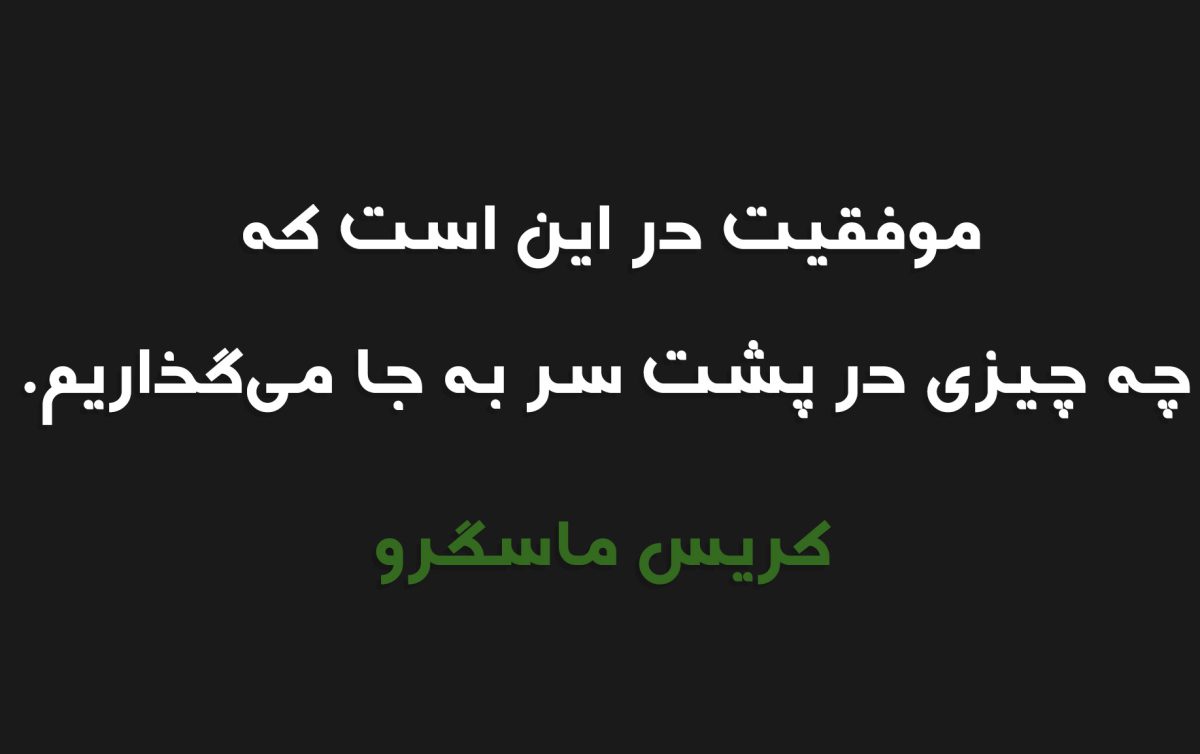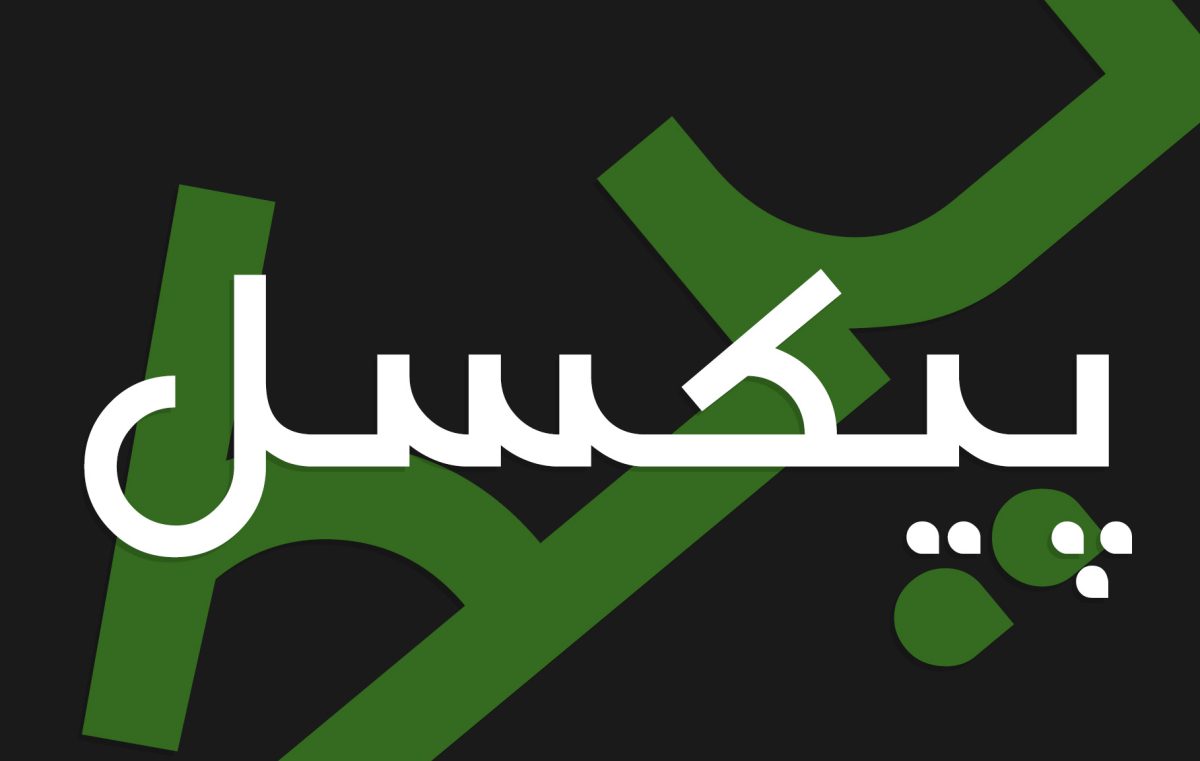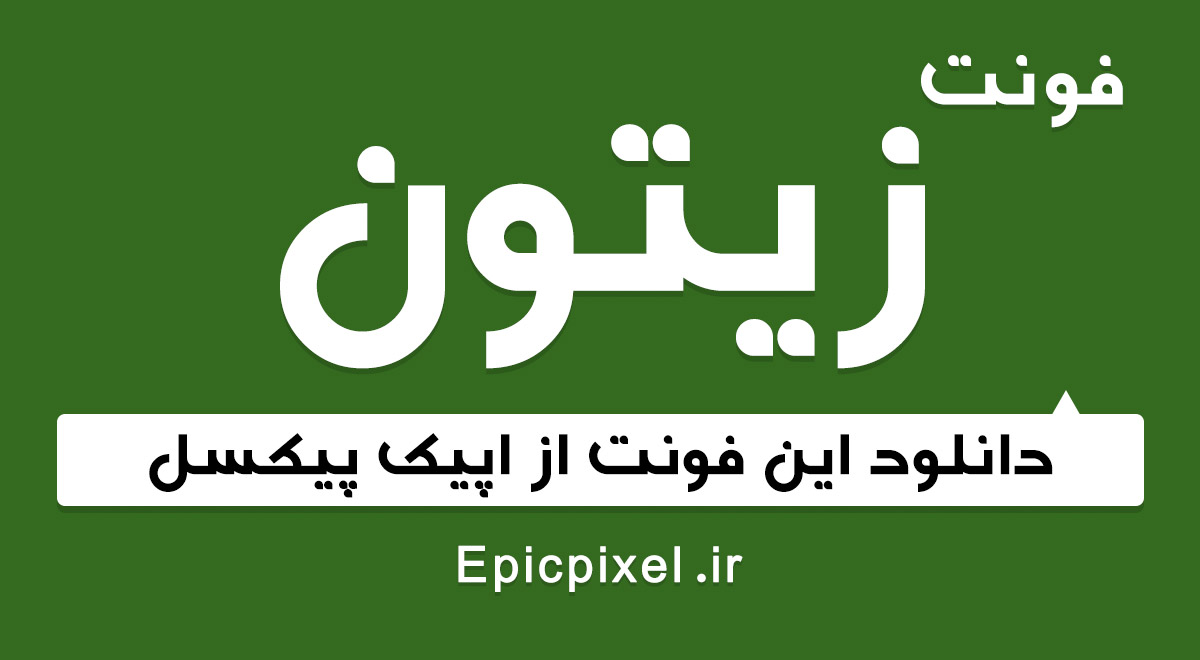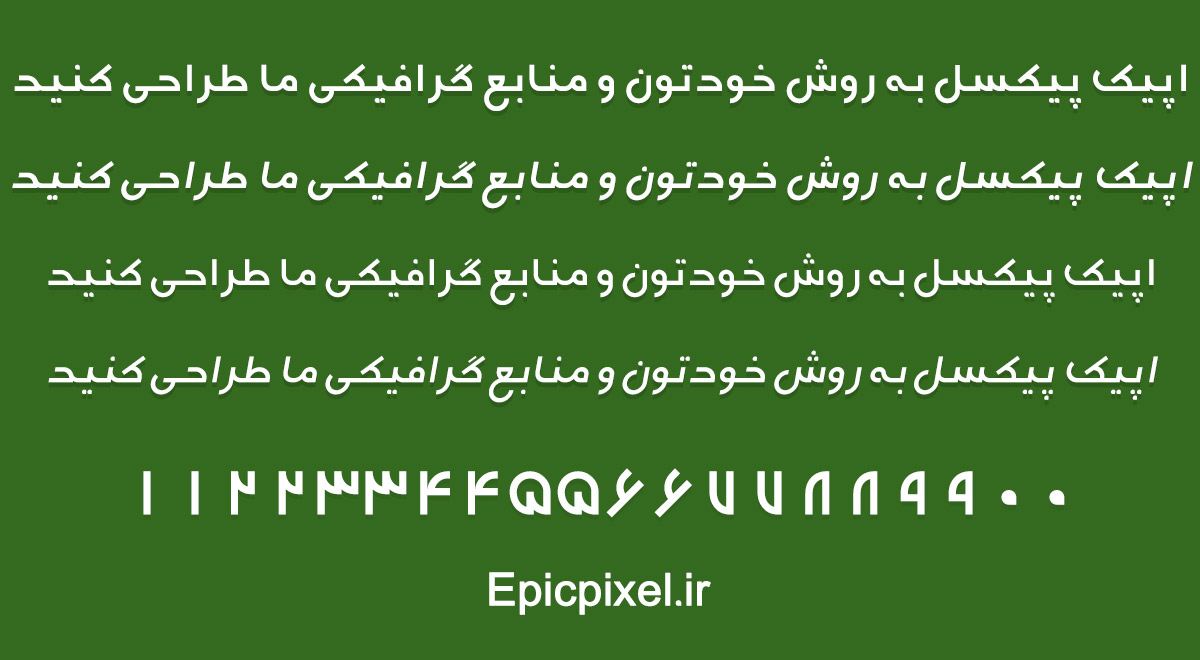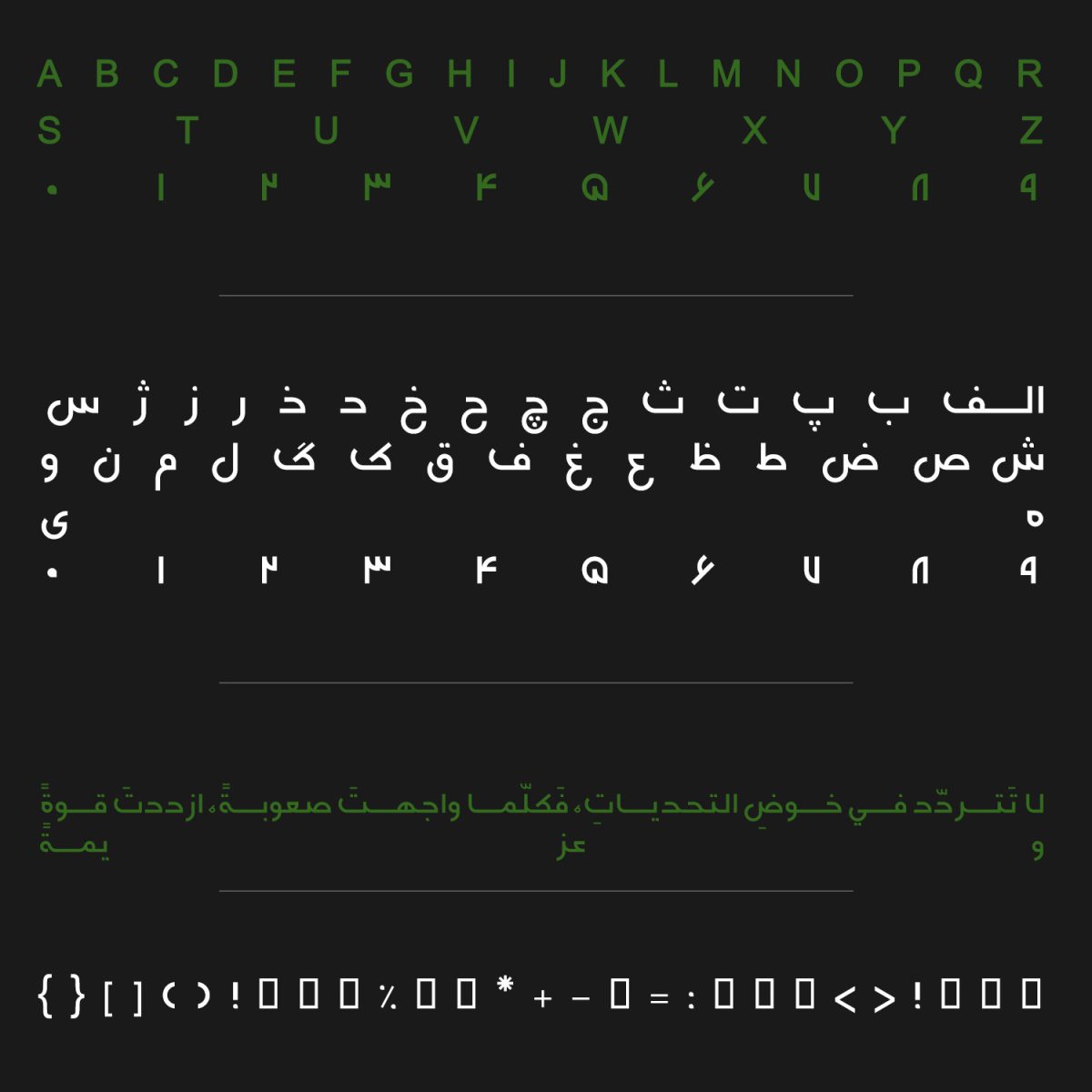
4 فونت زیتون فارسی Zeytoon
فونت فارسی زیتون، یک قلم دایره ای و فانتزی با طراحی زیبا و حرفه ای است که به صورت رایگان قابل دانلود می باشد. این فونت با پشتیبانی از تمام حروف و اعداد فارسی، در چهار حالت مختلف با اسامی متفاوت (F zeytoon Normal, IR Zeytoon Regular, W zeytoon Regular, Zeytoon Regular) ارائه شده است. فونت زیتون دارای خوانایی بالایی برای عناوین بوده و برای استفاده در لوگوتایپ، تایپوگرافی و انواع طراحی گرافیک، از جمله چاپ و امور تبلیغاتی، بسیار مناسب است. این قلم که قبلاً پولی بوده و هم اکنون رایگان شده، در فرمت TTF بر روی ویندوز، مک و موبایل قابل نصب و استفاده در تمامی نرم افزارهای گرافیکی است.
قلمی دایره ای، فانتزی و رایگان برای طراحی
فونت فارسی زیتون، یک قلم با ظاهر بصری متمایز و کارایی بالا برای طراحان است. این فونت با طراحی دایره ای و فانتزی خود، جلوه ای جالب و متفاوت به متون می بخشد و آن را برای پروژه هایی با حس خلاقیت و سبکی غیررسمی مناسب می سازد. این فونت زیبا و حرفه ای برای طراحی محسوب شده و یک فونت جالب و متفاوت برای خلق آثار خلاقانه است که می تواند به سرعت توجه مخاطب را جلب کند.
یکی از نکات قابل توجه در خصوص فونت زیتون، ارائه آن در چهار حالت مختلف با اسامی متفاوت است. این نسخه ها با نام های فونت اف زیتون نرمال (F zeytoon Normal)، فونت آی آر زیتون ریگولار (IR Zeytoon Regular)، فونت دبلیو زیتون ریگولار (W zeytoon Regular)، و فونت زیتون ریگولار (Zeytoon Regular) در دسترس هستند. این حالت های مختلف، نسخه های گوناگون این فونت را شامل می شوند، از جمله نسخه با پسوند IR که به عنوان “نسخه سالم” (اصلاح شده توسط شورای عالی اطلاع رسانی) معرفی شده است که از نظر فنی بهینه شده است. وزن آن عموماً معمولی – Regular می باشد که پرکاربردترین وزن برای بسیاری از طراحی ها است.
دانلودفونت زیتون به واسطه خوانایی بالا که دارد، به صورت ویژه برای استفاده در لوگوتایپ، تایپوگرافی و همچنین در عناوین مختلف بسیار مناسب است و پیام را با ظاهری دایره ای و دلنشین منتقل می کند و در اندازه های مختلف عملکرد خوبی دارد. این قلم یک فونت گرافیکی و حرفه ای برای انجام امور خاص طراحی و نیز برای طراحی های گرافیکی و چاپ به صورت کلی می باشد و ابزاری منعطف برای نیازهای متنوع است.
این فونت گرافیکی و حرفه ای دارای تمام حروف و اعداد فارسی است که امکان استفاده کامل از آن را در محتوای فارسی بدون هیچ نقصی فراهم می کند و آن را به ابزاری کاربردی برای طراحان فارسی زبان تبدیل می کند. فونت زیتون با فرمت ttf ارائه می شود که سازگاری بالایی با نرم افزارهای طراحی و سیستم عامل ها دارد و نصب و استفاده از آن را بسیار آسان می کند.
کاربردهای فونت زیتون در طراحی گرافیک و چاپ
با توجه به طراحی دایره ای و فانتزی، خوانایی بالا، و قابلیت استفاده در انواع نرم افزارهای گرافیکی، فونت زیتون کاربردهای متنوعی در طراحی گرافیک و چاپ دارد و برای خلق آثاری با جلوه ای شاداب و دلنشین مناسب است. این قلم زیبا و حرفه ای برای استفاده در لوگوتایپ، تایپوگرافی و عناوین مناسب است. همچنین برای طراحی انواع کارت ویزیت ، بروشور ، تراکت ، پوستر ، طرح های تبلیغاتی و … که نیاز به فونتی جذاب و گویا دارند، کاربرد دارد. فونت زیتون یک فونت گرافیکی و حرفه ای برای انجام امور خاص طراحی و نیز برای طراحی های گرافیکی و چاپ به صورت کلی می باشد و برای طراحان وب سایت و گرافیست های خلاق در طراحی پروژه های تبلیغاتی و تجاری به زبان فارسی قابل استفاده است. این فونت به سادگی در نرم افزارهای تحت ویندوز از جمله مجموعه برنامه های CorelDRAW, Office, Adobe و …. قابل اجرا می باشد.